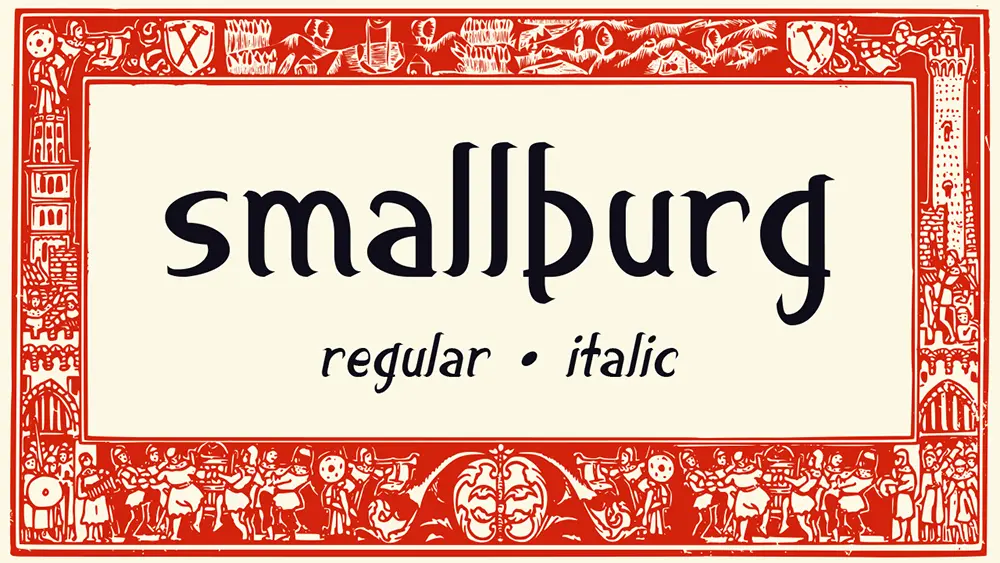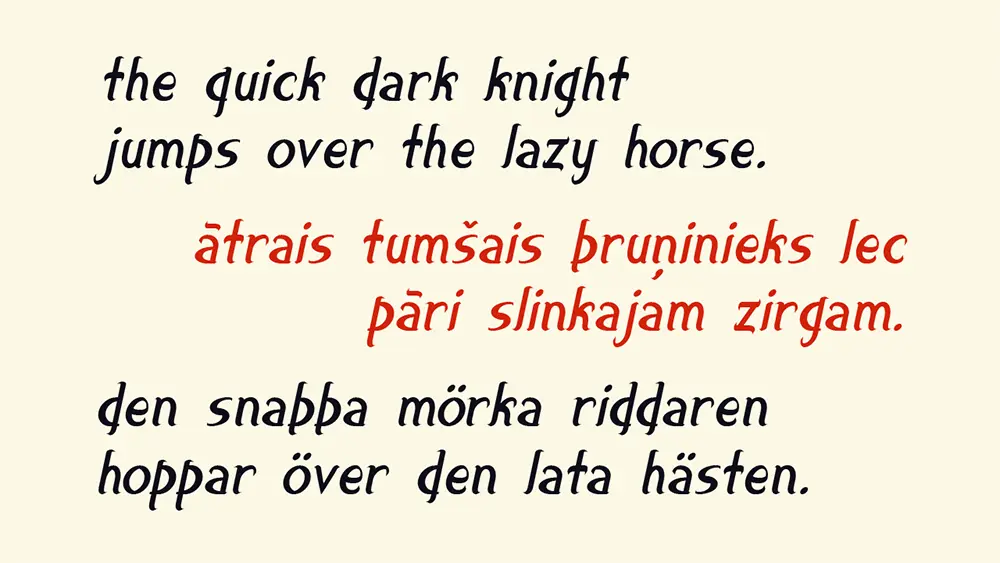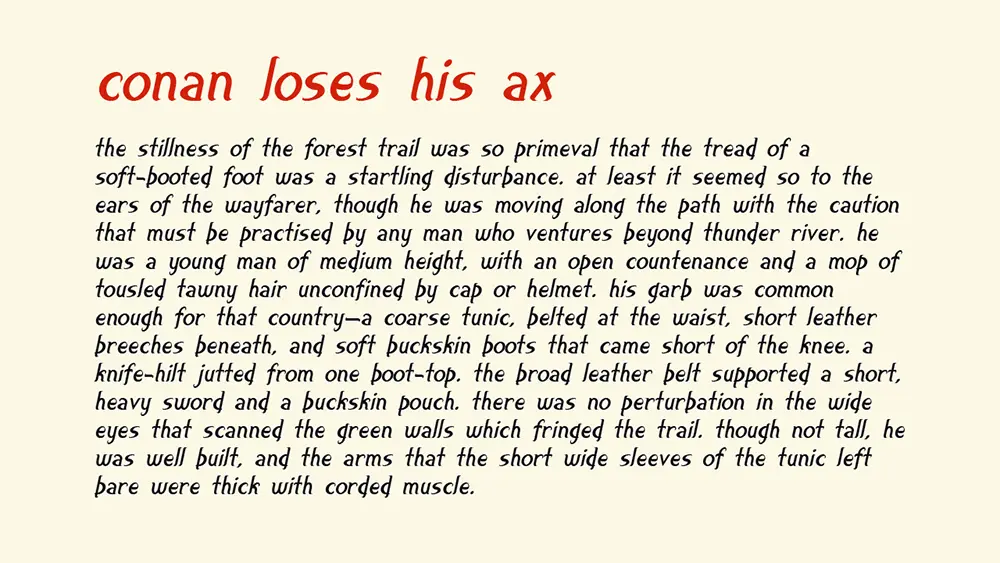
Smallburg介紹
Smallburg是一款根據SIL OFL協議發佈的免費英文字體,手寫風格,字母僅限小寫(輸入大寫字母仍然顯示小寫),包含 2 種樣式(Regular、Italic)和 457個字形。
支持 45 種語言:阿爾巴尼亞語、羅馬尼亞語、阿斯圖里亞斯語、布列塔尼語、加泰羅尼亞語、克羅地亞語、捷克語、丹麥語、荷蘭語、英語、世界語、愛沙尼亞語、芬蘭語、法語、加告茲語、德語、匈牙利語、冰島語、伊博語、印度尼西亞語、意大利語、Khoekhoe、拉科塔語、拉丁語、拉脫維亞語、立陶宛語、馬耳他語、馬普頓貢語、北薩米語、挪威語、波蘭語、葡萄牙語、羅馬尼亞語、蘇格蘭蓋爾語、斯洛文尼亞語、西班牙語、瑞典語、他加祿語、土耳其語、沃爾瑟德語、威爾士語、西弗里斯蘭語、扎扎基語、祖魯語。